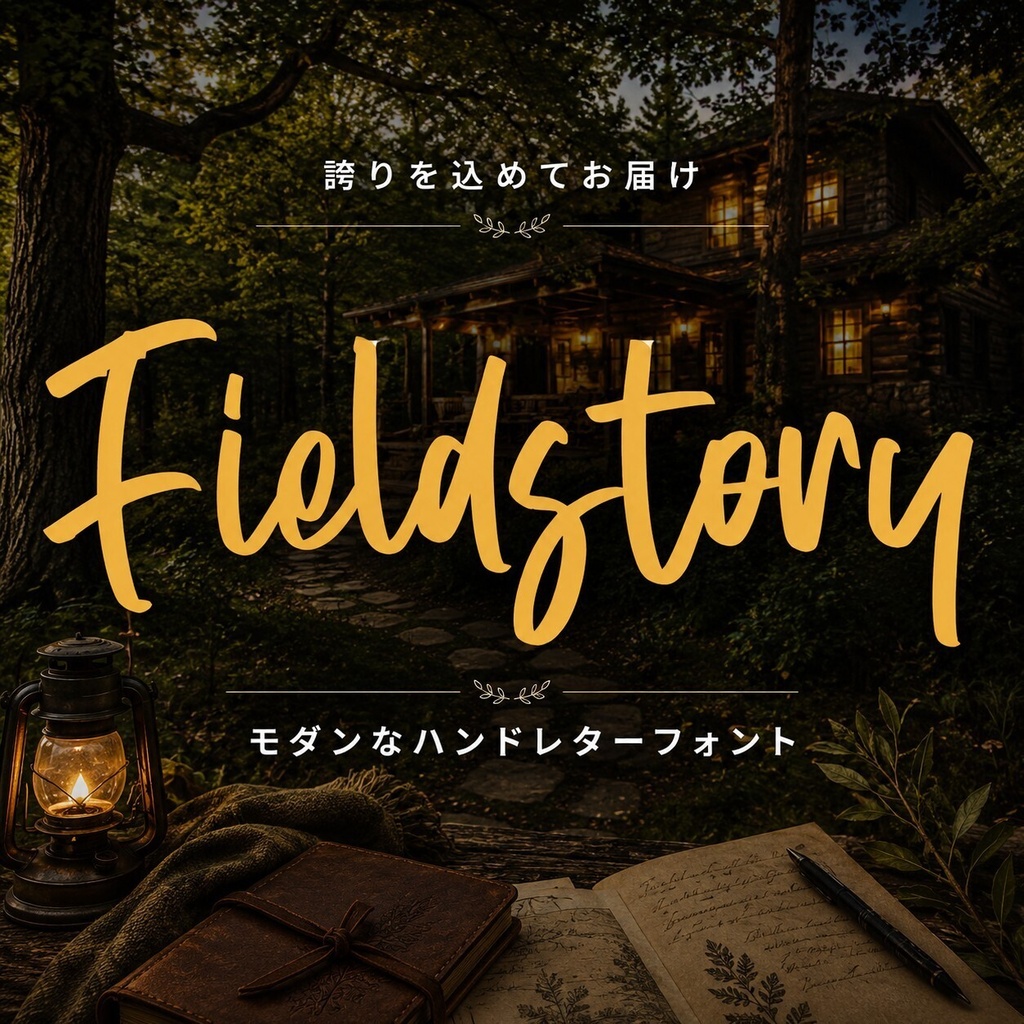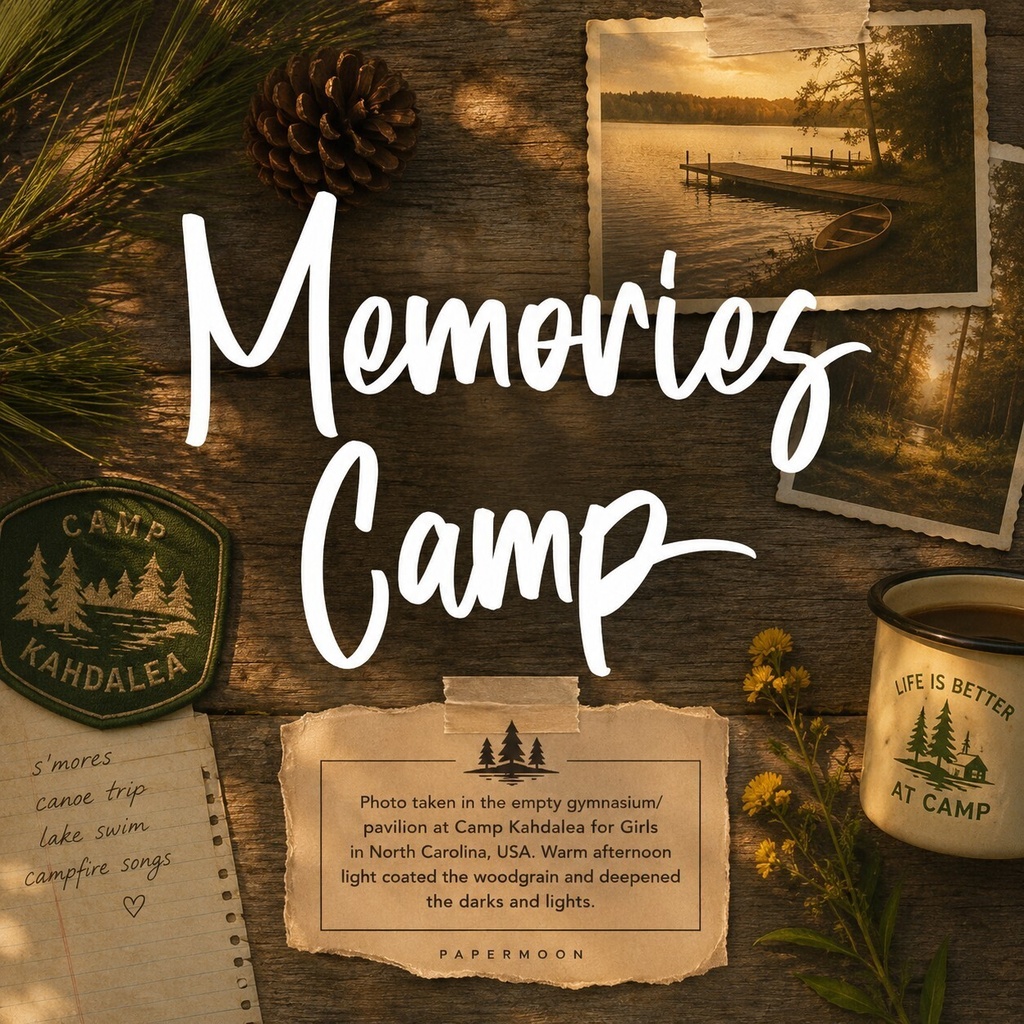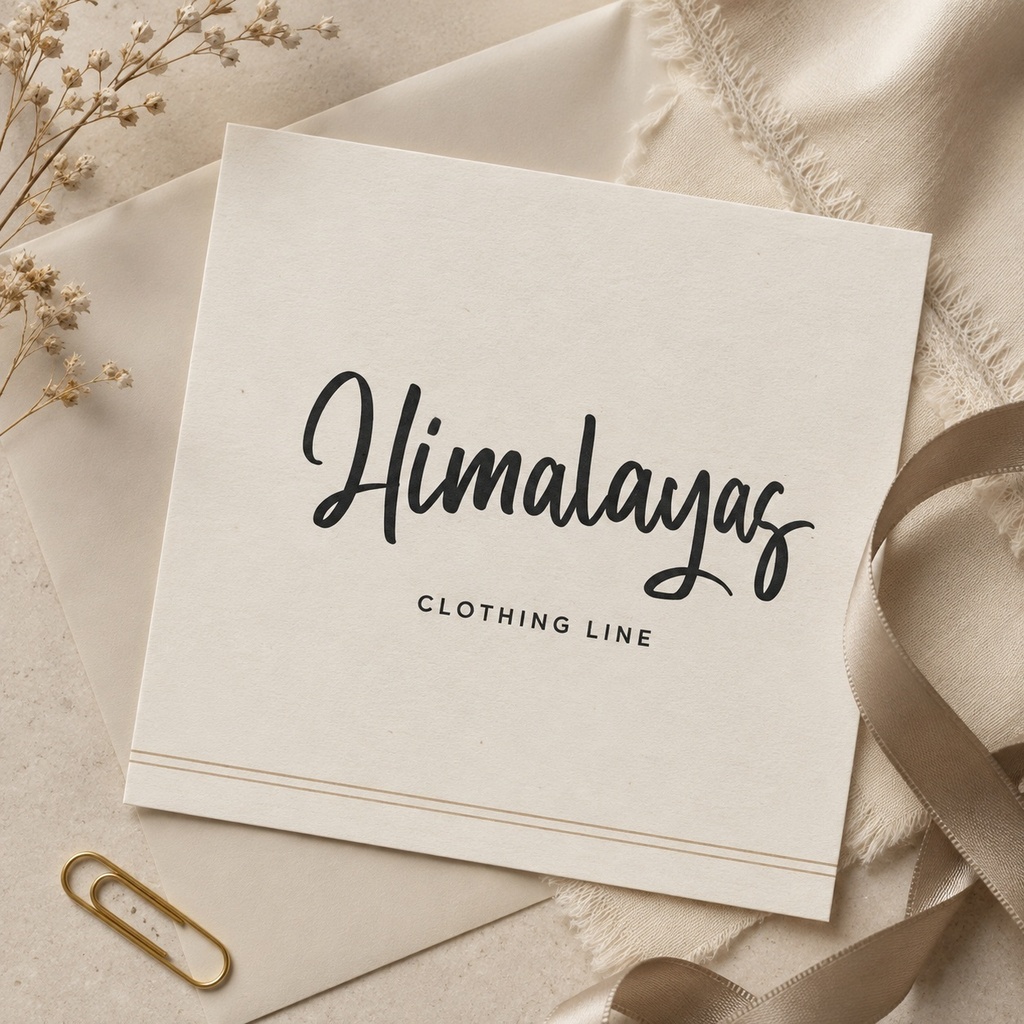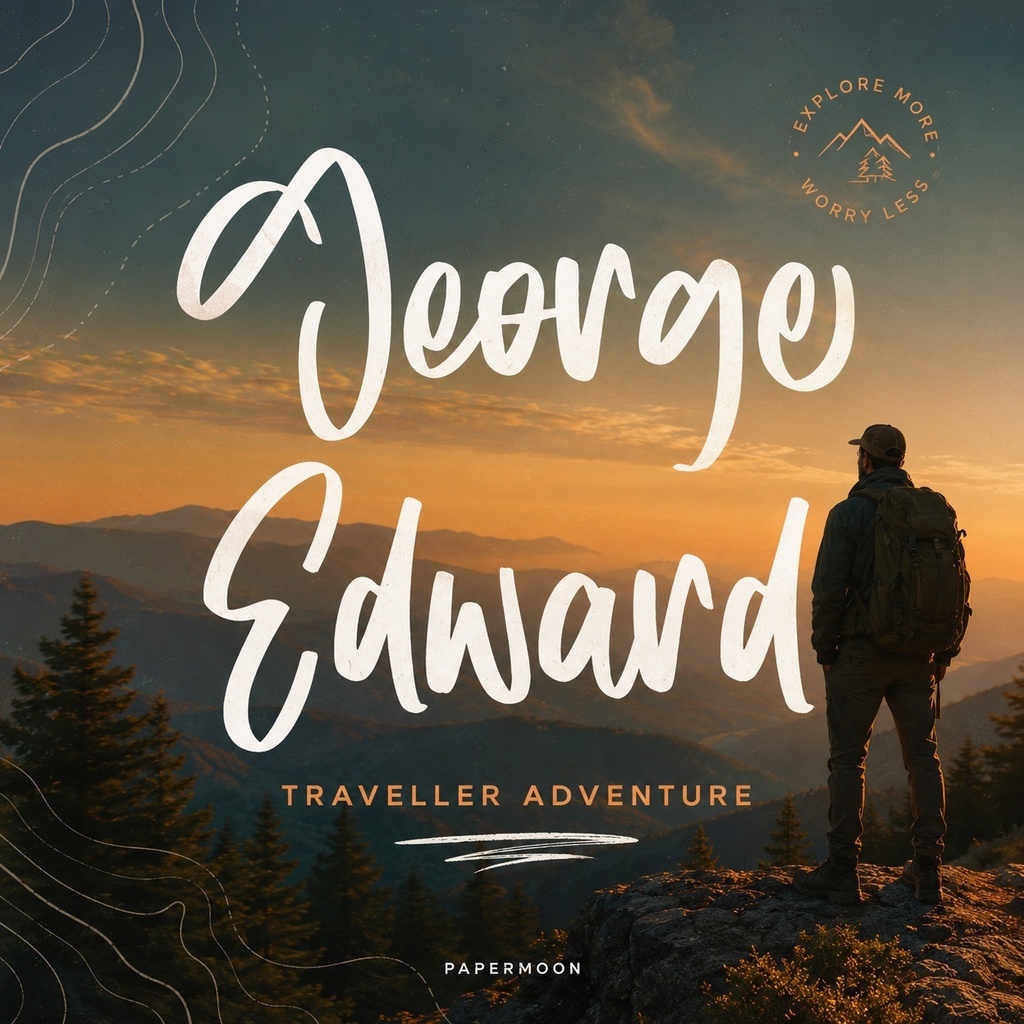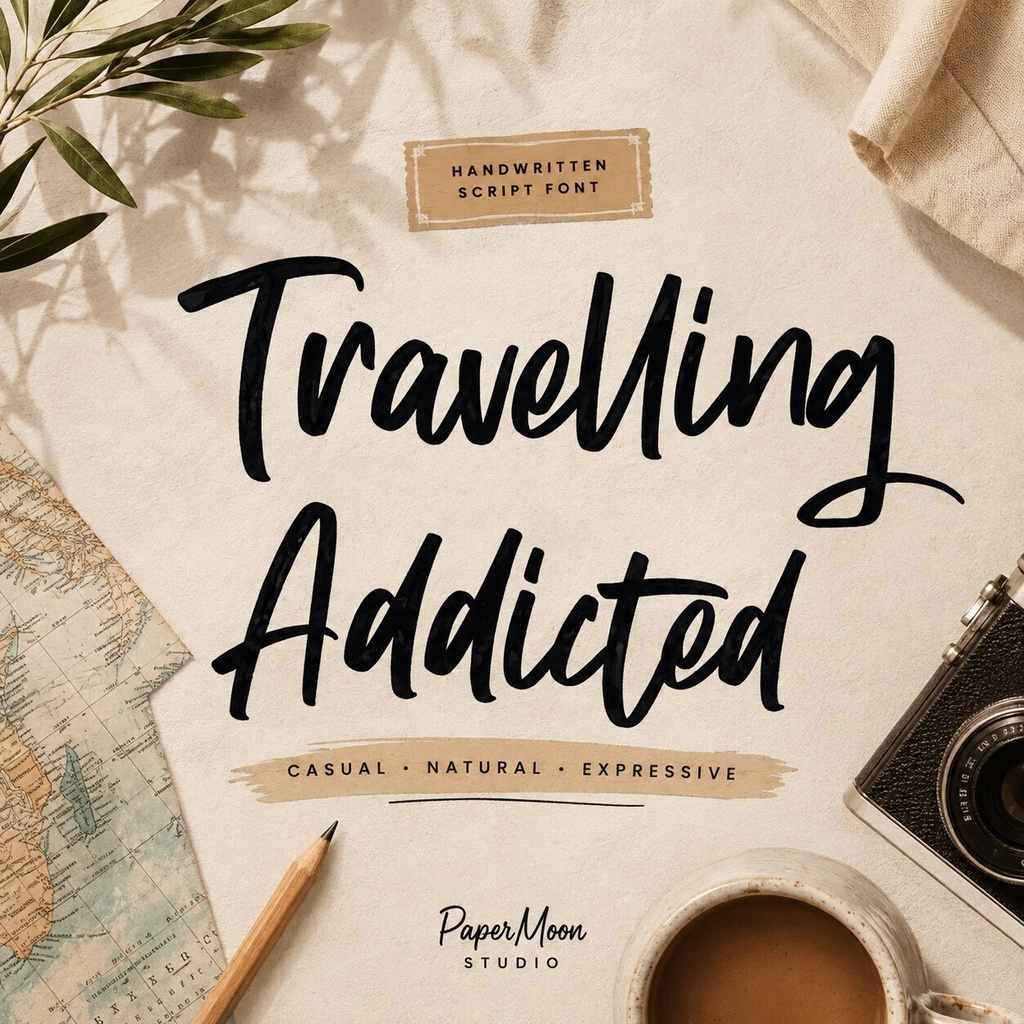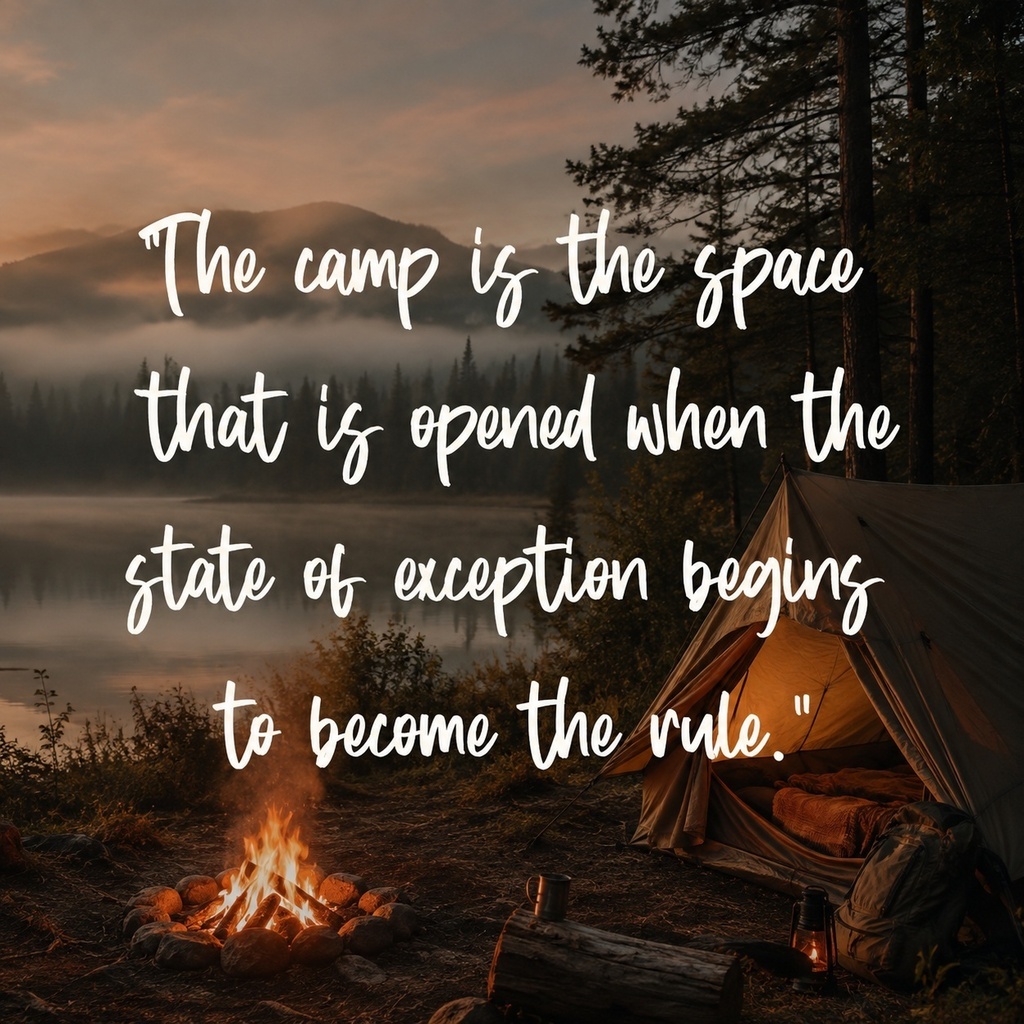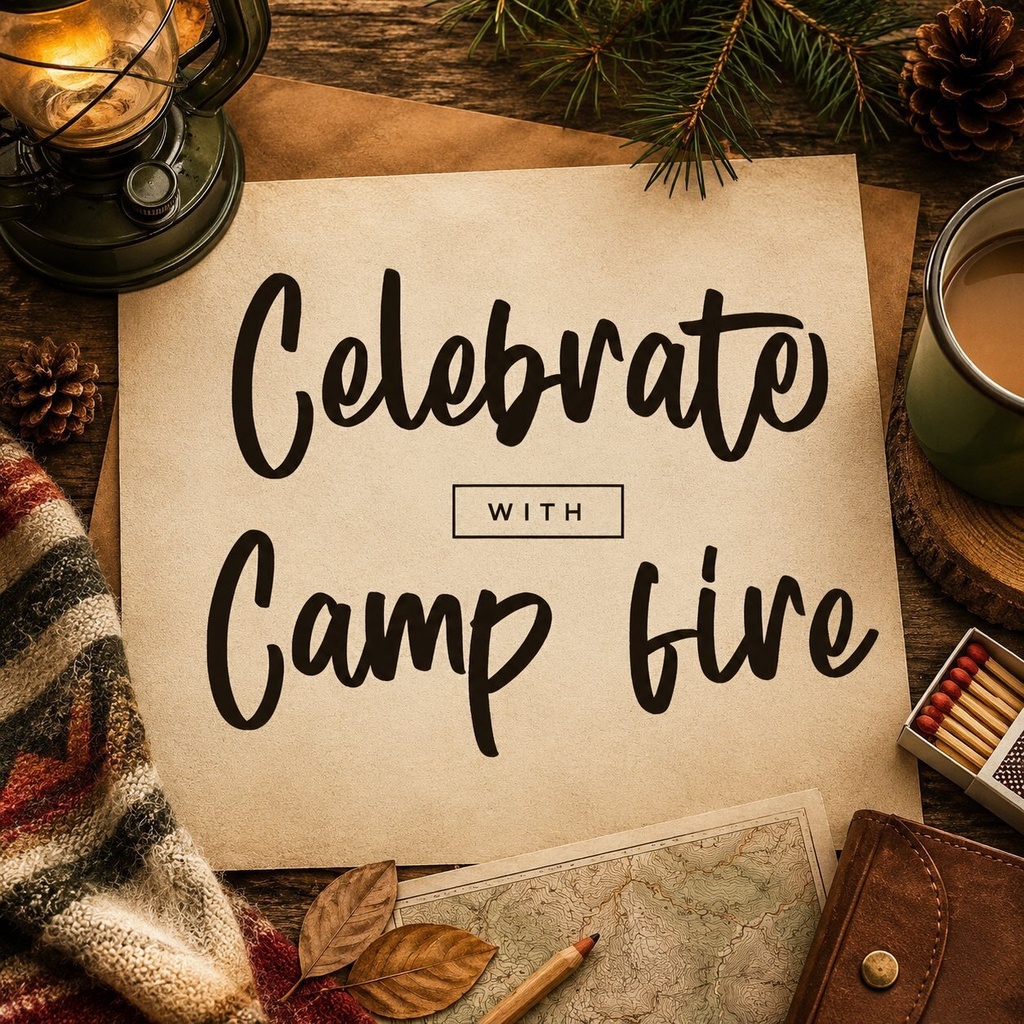
FieldStory | 手書き風のエレガントな欧文フォント | Hand Lettering Font
FieldStoryは、伝統的なエレガンスに現代的な軽やかさを加えた、手書き風の欧文フォントです。なめらかで洗練されたストローク、エレガントな手書き感、読みやすいミニマルな印象、太細のコントラスト、控えめなカーブが、文字に上品な表情を与えます。 ウェディングの招待状、ロゴ、ブランディング、ソーシャルメディア用グラフィック、ポスターなど、短い見出しや印象的な文字組みにおすすめです。クラシックな雰囲気と現代的な読みやすさを両立したいデザインにご利用ください。 ### 収録内容 - FieldStory - リガチャ、スタイル代替、アクセント文字、多言語対応 - 大文字・小文字、数字、句読点、記号 ### 対応文字 ラテン文字を中心とした欧文向けです。アクセント文字と多言語対応を含みますが、日本語・キリル文字・ギリシャ文字の収録については確認済みの情報がないため、必要な文字は購入前にご確認ください。 ### 用途 ウェディング招待状、ロゴ、ワードマーク、ブランディング、ソーシャルメディア画像、ポスター、見出し、カード、ステーショナリーなど。 ### 形式 OTF / TTF ### 対応環境 MacおよびWindowsに対応します。Photoshop、Illustrator、その他のフォント対応デザインアプリケーションでご利用いただけます。リガチャやスタイル代替の表示方法はアプリケーションによって異なります。 ### 利用許諾 商用利用版と個人利用版の2種類を用意しています。具体的な利用範囲、再配布、埋め込み、再販などの条件は、購入する variant に付属するライセンス本文をご確認ください。 FieldStoryで、招待状やロゴ、ブランドの見出しに、上品で自然な手書きのリズムを加えてください。